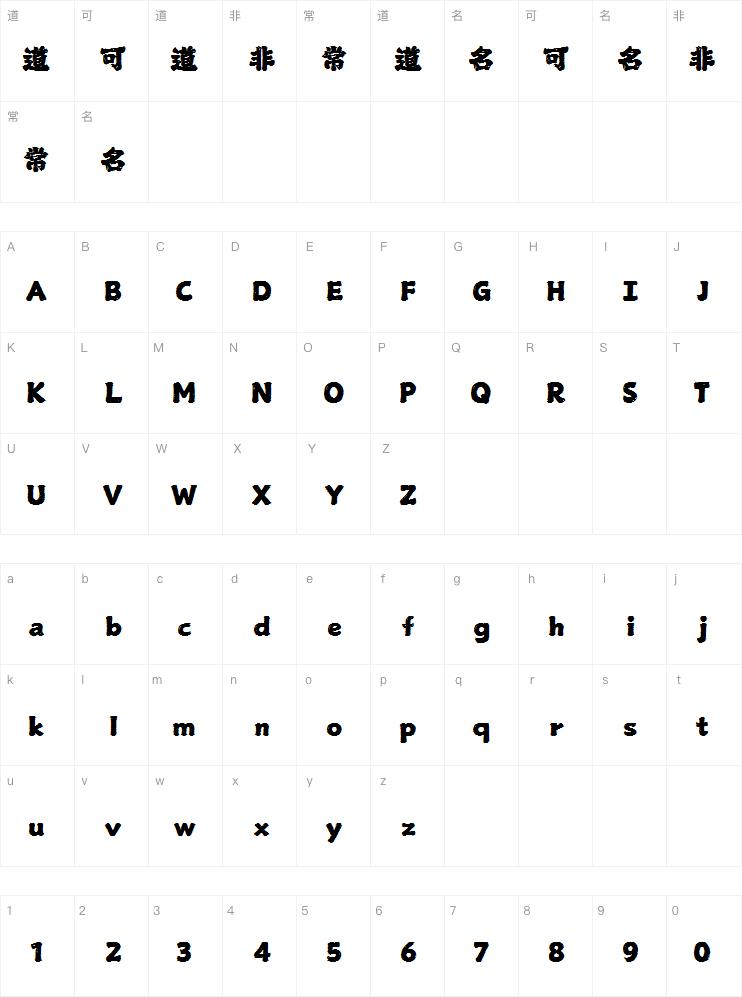
山海福瑞手书,是一款全新的毛笔风字体,包含汉字9169个,符号200+个。该字体的毛笔笔锋狂野有力,,非常醒目!字形古朴浑厚,在浑厚的同时而又极富张力。它的笔画充满力量感的同时,用蕴含着朴拙感。在粗细的纵横间,拥有非常规的张力特性。笔画的飞白效果使字体的气息更加流畅,笔画间的关系密不可分,同时也增加了字体的自由洒脱之感。